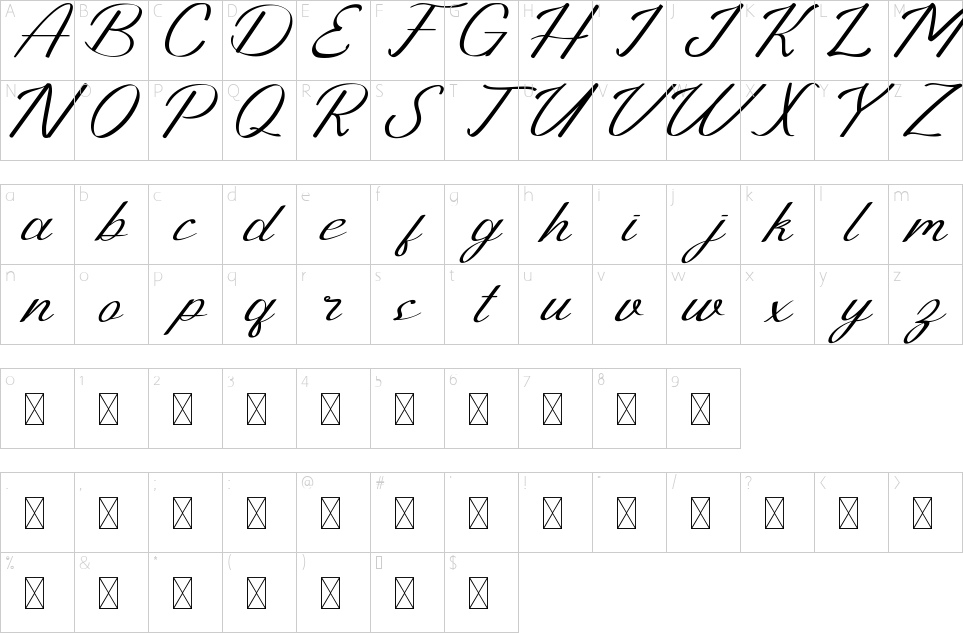
Preproduction é uma fonte moderna e versátil que está disponível gratuitamente tanto para sistemas Windows quanto Mac. Ela foi criada pelo designer desconhecido RaisProject, e desde seu lançamento, já foi baixada pelo número impressionante de 3.770 usuários. Esta fonte é perfeita para projetos de preprodução, gráficos digitais e até mesmo para textos no meio editorial. Seja para dar um toque criativo em seu design gráfico, ou para personalizar o texto de suas páginas web, Preproduction é uma escolha confiável e gratuita. Adicionar esta fonte a sua biblioteca de recursos gráficos pode dar um toque diferenciado a qualquer projeto.